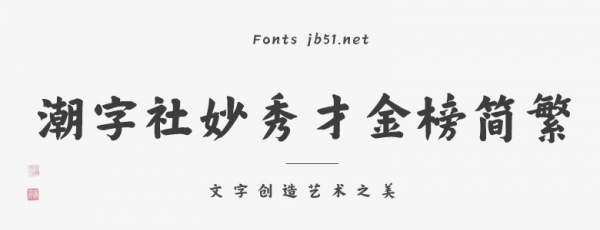
潮字社妙秀才金榜簡繁是一款古典文雅的榜書字體,宏偉大氣,將端莊大方的古典氣息與靈動潮流的現(xiàn)代感巧妙結(jié)合,字形規(guī)整,但部分筆畫又脫離了刻板的標準規(guī)范,適合于文化類的宣傳設(shè)計、商業(yè)類品牌的廣告和產(chǎn)品包裝設(shè)計以及個性化文字排版等較多場景。